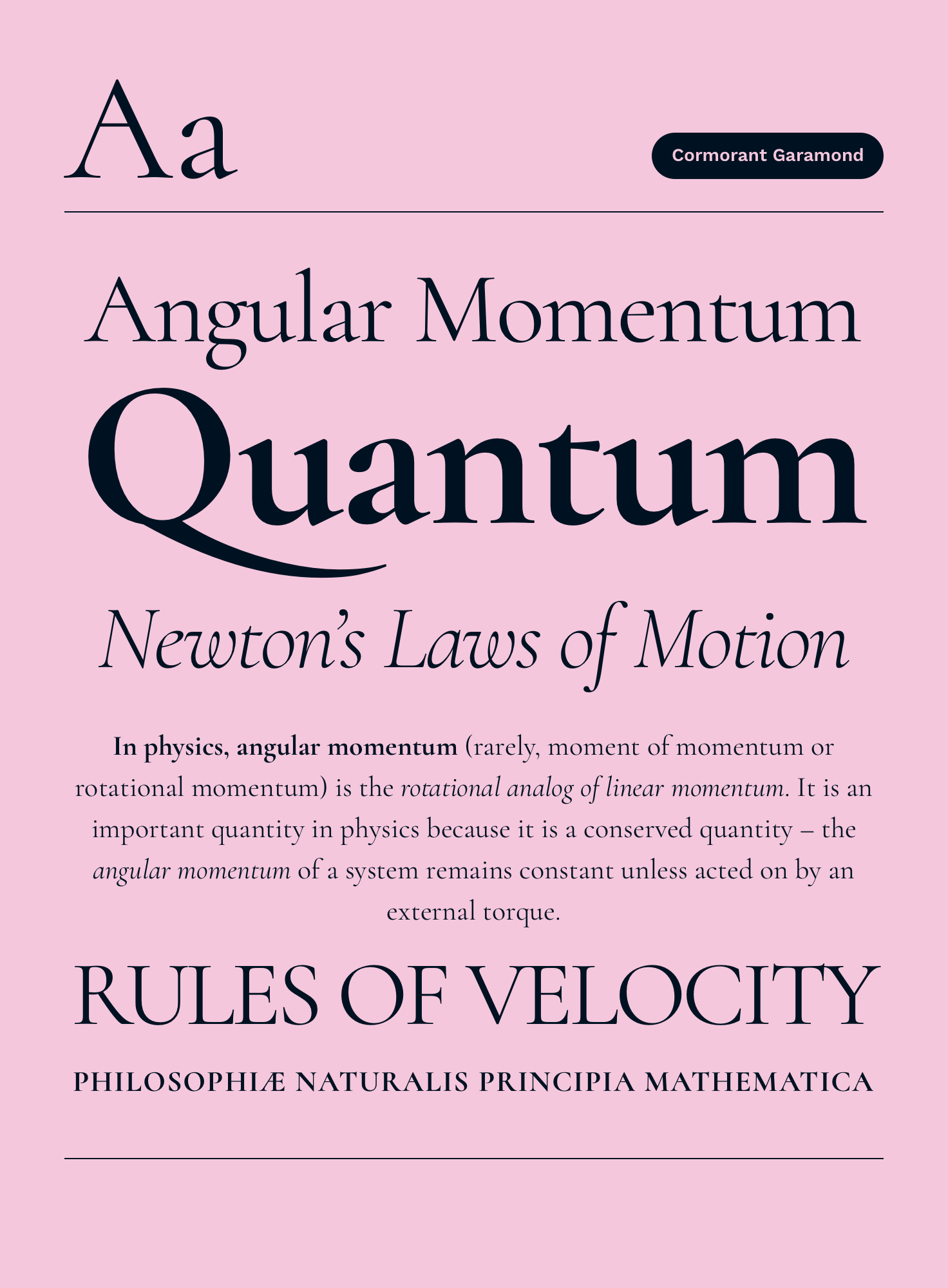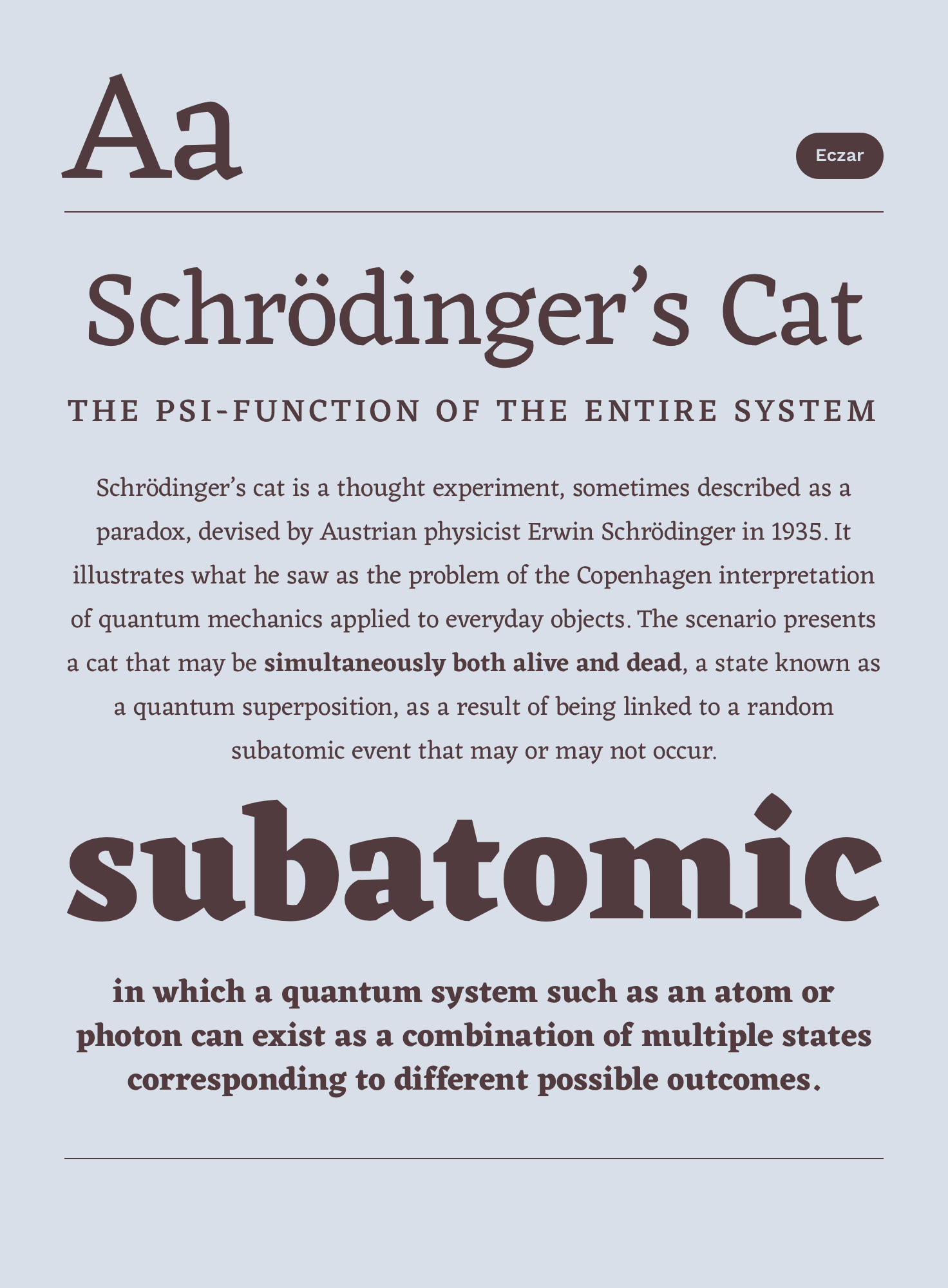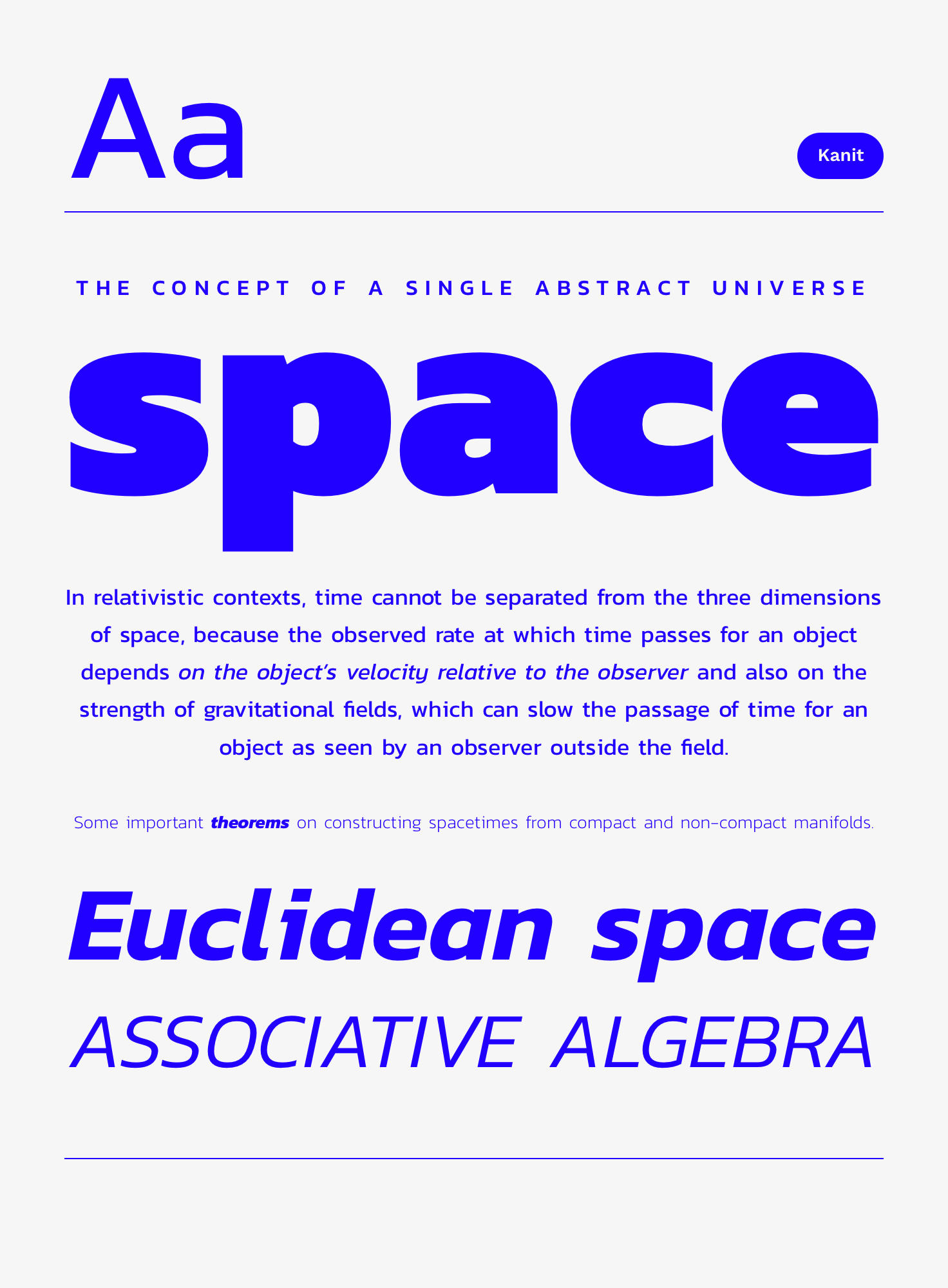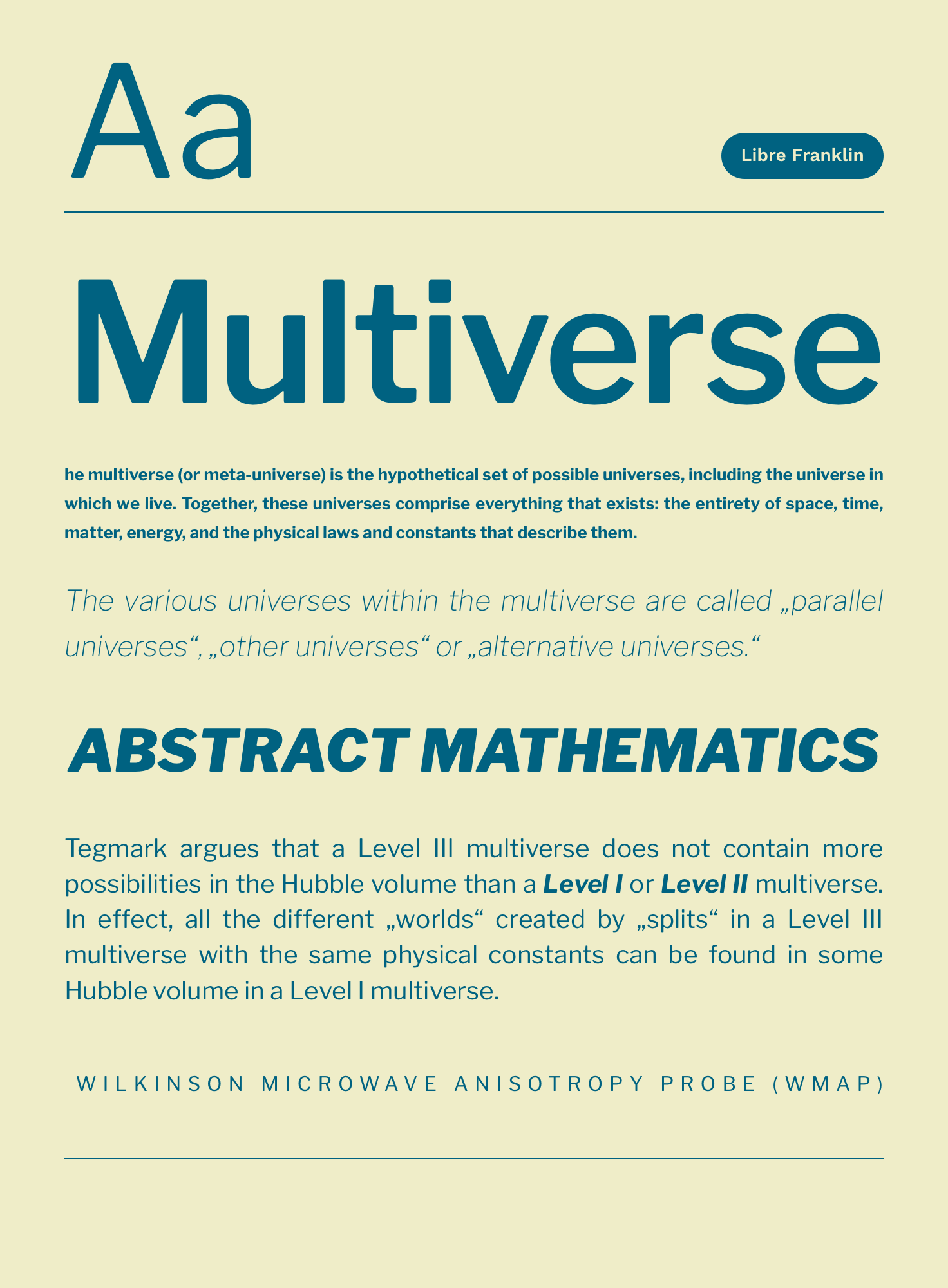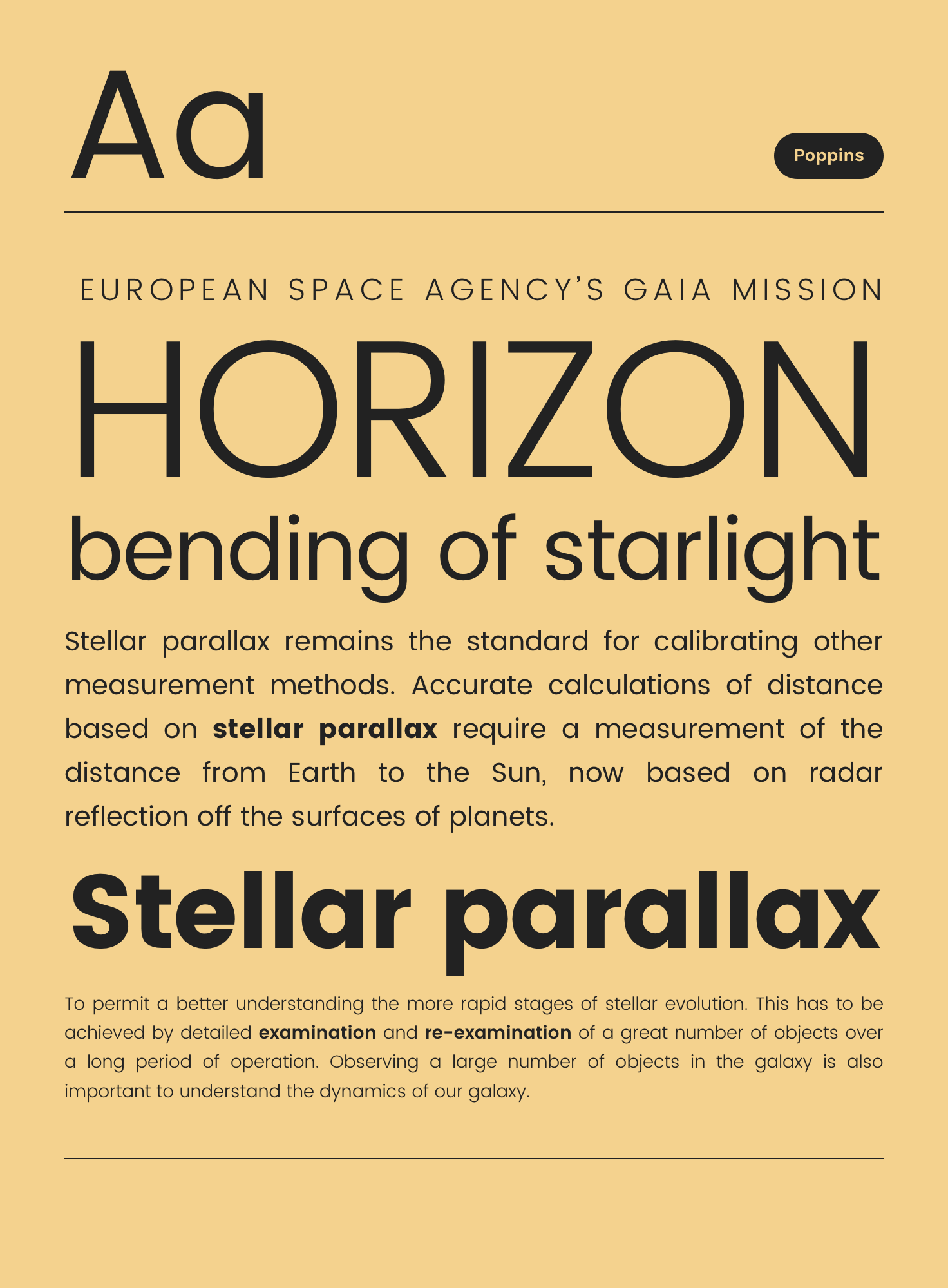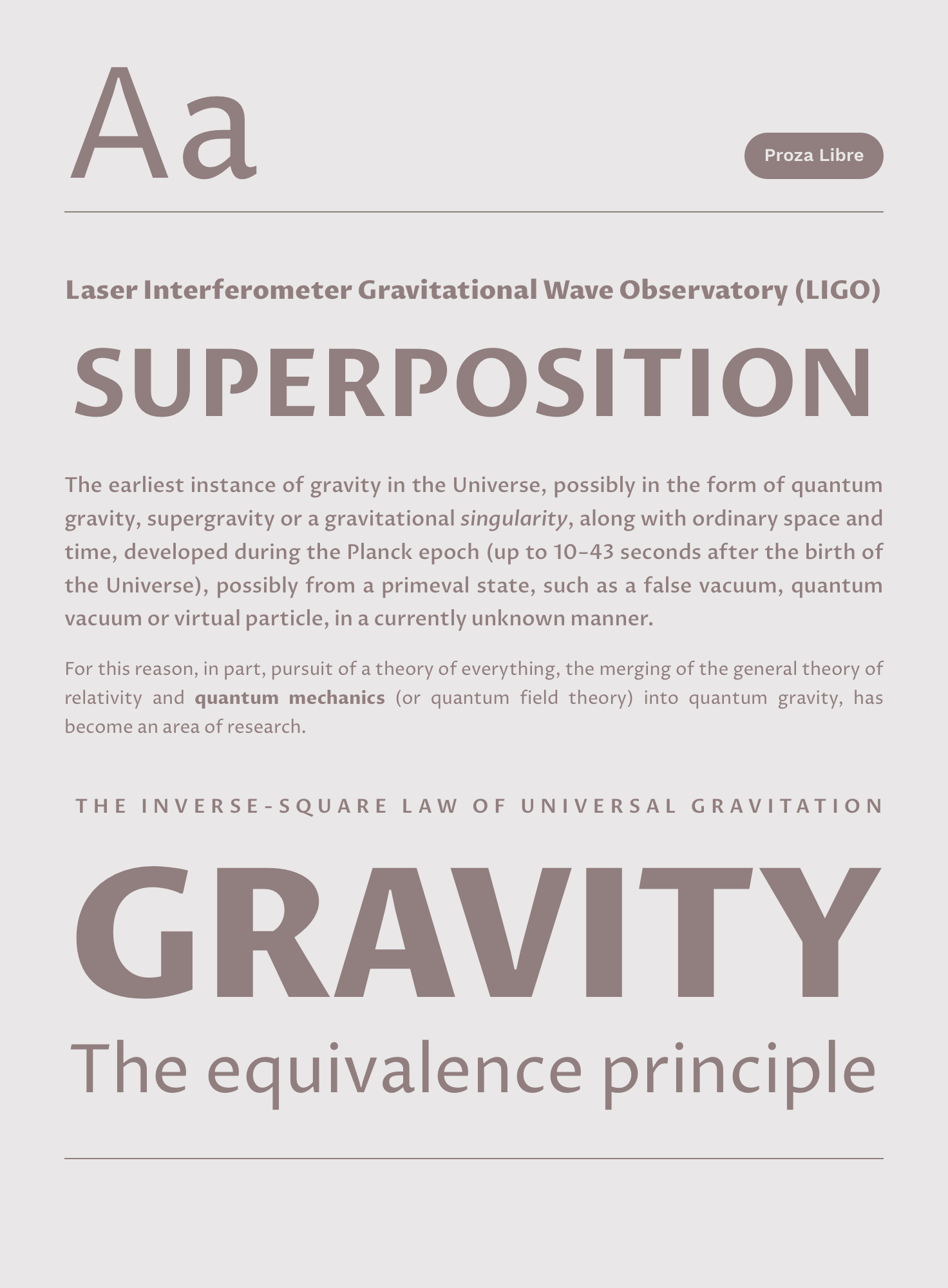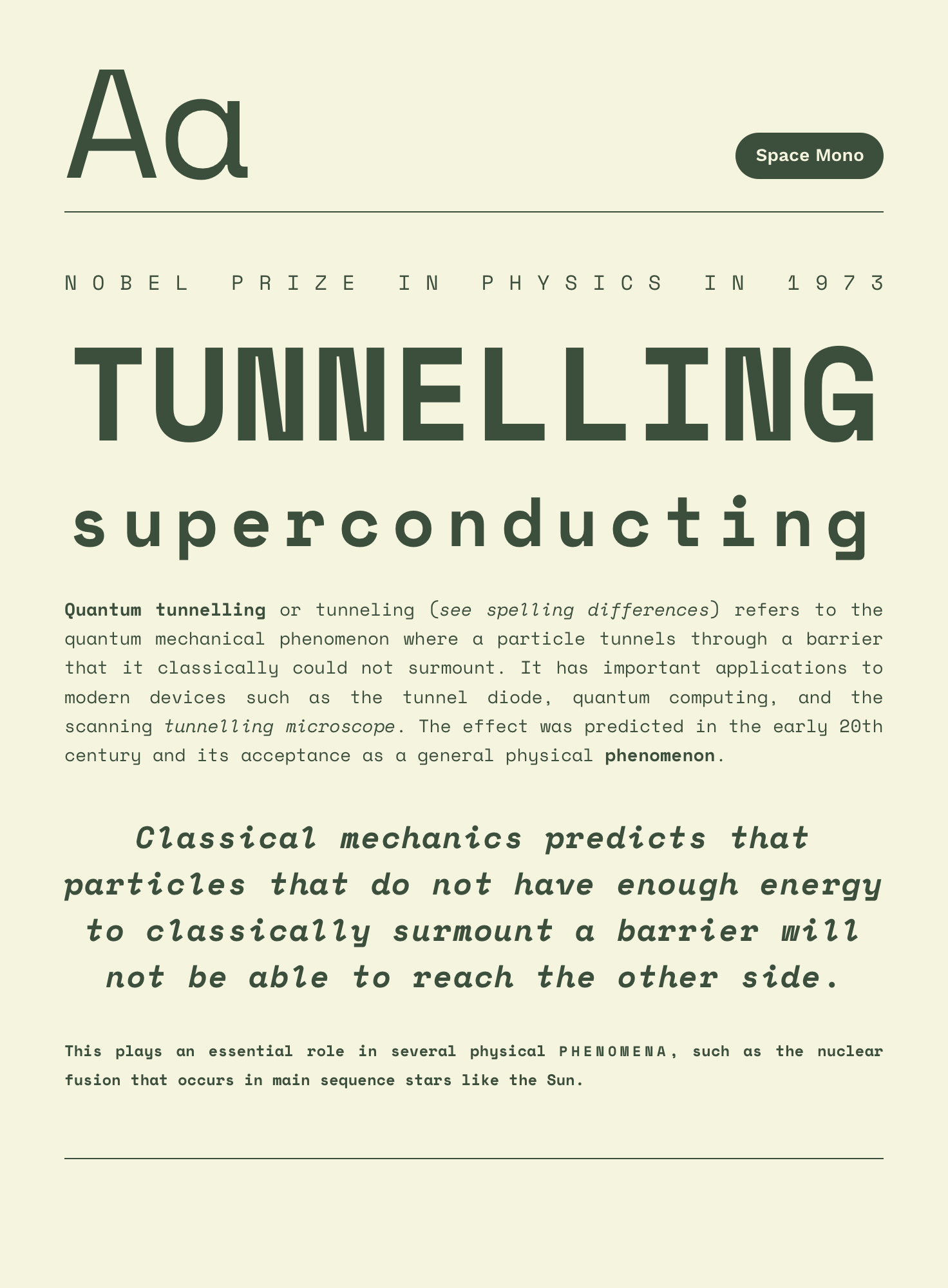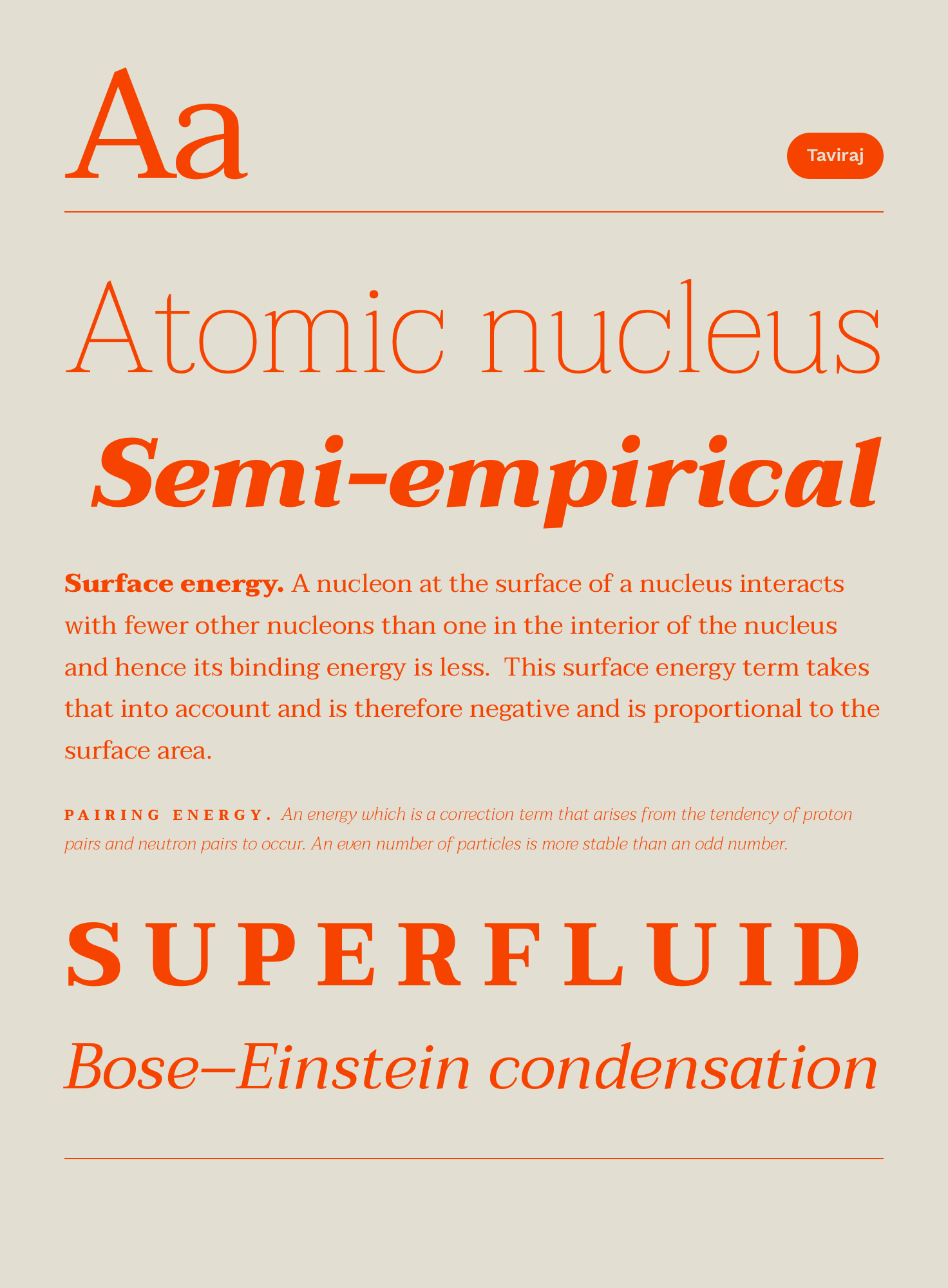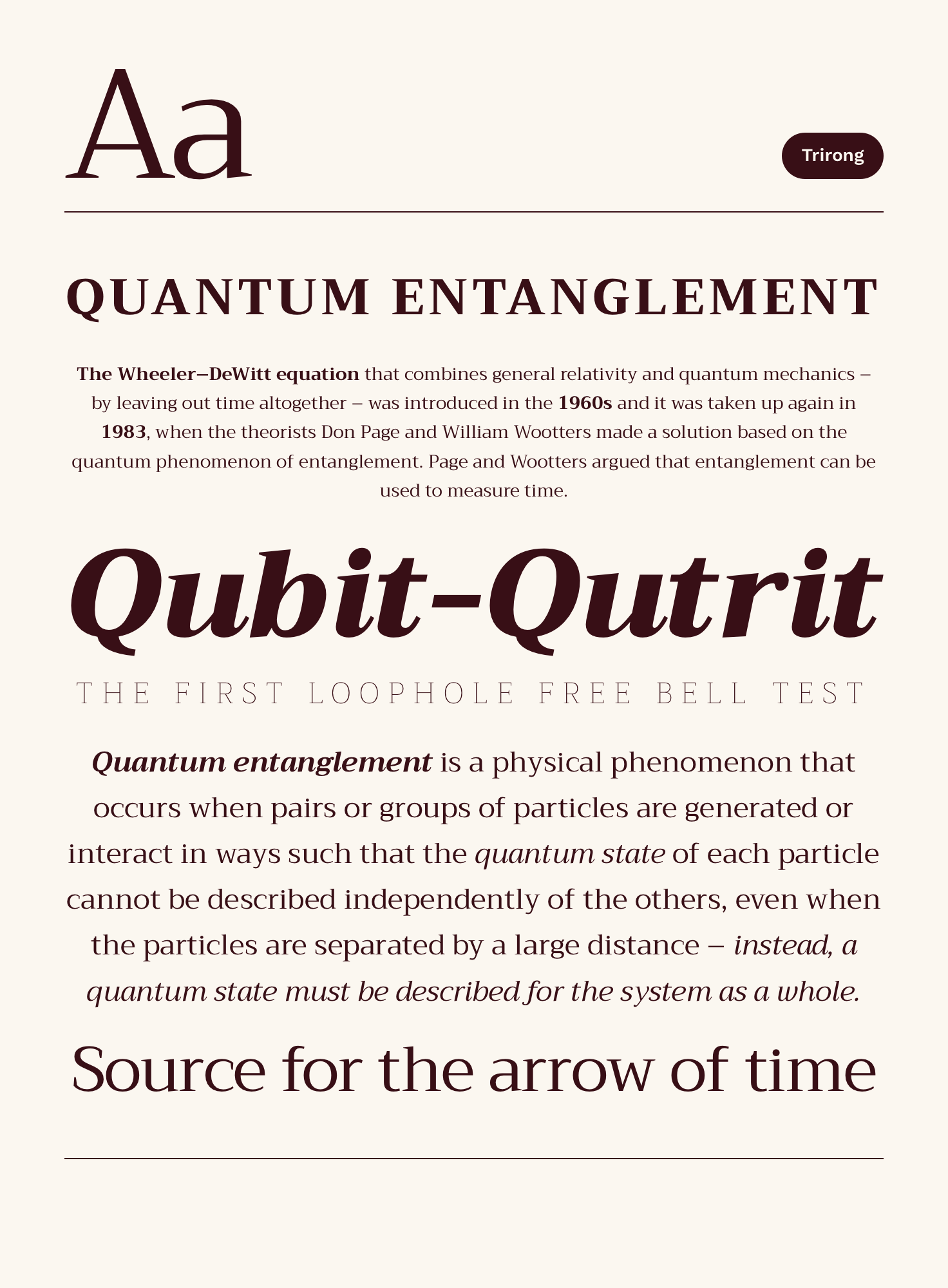
Es gibt jede Menge wunderschöne Google Fonts, aber da es inzwischen über 800 Schriften auf Google Fonts zur Auswahl gibt, kann es schwierig werden die passende Schrift für eine Webseite zu finden. Viel zu oft sieht man die gleichen Schriften im Einsatz, daher haben wir eine Liste weniger häufig verwendeter Google Fonts für dich zusammen gestellt. Hier sind unsere Google Fonts Favoriten, die du in 2017 unbedingt ausprobieren solltest.
1. Cormorant Garamond
Das Besondere an der Cormorant Garamond (neben dem Fakt, dass es eine sehr schöne, elegante Serifenschrift ist) ist, dass die Schrift eine große Anzahl an verschiedenen Schriftschnitten hat. Es gibt insgesamt 45 verschiedene Versionen der Schrift, einen Überblick findet man auf der Bēhance Seite der Schrift. Wir haben Cormorant Garamond auch im neuesten Designstil (siehe Live Demo Ruapuke) unseres Uku-Themes verwendet.
2. Proza Libre
Proza Libre ist die kostenlose Light-Version der Schrift Proza von Jasper de Waard (vom Bureau Roffa), eine von der Garamond Sans inspirierte elegante serifenlose Schrift. Die Schrift ist sehr angenehm lesbar als Fließtext und hat einen eleganten Stil in Titelschriftgrößen. Im Blogbeitrag “Proza’s Story” auf I Love Typography kannst du mehr über die Entstehungsgeschichte von Proza lesen.
3. Trirong
Trirong ist eine markante Serifenschrift mit 16 Schriftstilen der thailändischen Font Foundry Cadson Demak. Die Schrift ist recht breit und rund, ein Stil der der thailändischen Schrift nachempfunden ist. Die Schrift ist durch ihre Breite sehr gut als Fließtext lesbar.
4. Libre Franklin
Libre Franklin ist eine Neuinterpretation der klassischen amerikanischen Sansserif-Schrift “Morris Fuller Benton classic” der argentinischen Type Foundry Impallari Type. Libre Franklin hat 18 Schriftschnitte, was die Schrift sehr flexibel im Einsatz macht.
5. Taviraj
Auch Taviraj ist eine Schrift von Cadson Demak aus Thailand. Die moderne, vielseitig einsetzbare Serifenschrift mit 18 Schriftschnitten ist ähnlich wie Trirong von den klassischen, runden geschwungenen Buchstaben der thailändischen Schrift inspiriert.
6. Eczar
Die markante, eckige Schrift Eczar von Rosetta lässt sich wunderschön als Schrift für besondere Überschriften oder kleinere Textabsätze einsetzen. Besonders die fetten Schriftschnitte sind sehr charakterstark. Eczar gibt es in 5 Schriftschnitten.
7. Work Sans
Work Sans ist eine unserer persönlichen serifenlosen Schrift-Favoriten, die wir auch in unserem 2016 Elmastudio-Webdesign eingesetzt haben. Durch die Breite der Schrift ist Work Sans sehr gut lesbar und eignet sich daher besonders gut für Fließtexte im Web. Die Schrift von Wei Huang hat neun unterschiedliche Schriftschnitte.
8. Space Mono
Space Mono ist eine Monospace-Schrift von Colophon Foundry, die sich für individuelle Überschriften oder Meta-Text auf Webseiten besonders gut eignet. Die Schrift hat vier Schnitte, u.a. eine italic und bold italic.
9. Poppins
Poppins ist eine modern wirkende, geometrische serifenlose Schrift, die sowohl für Fließtexte, als auch für Überschriften sehr gut verwendet werden kann. Poppins ist von der Indian Type Foundry entwickelt und kann daher auch in Devanagari Schriftzeichen (für Sanskrit oder Hindi) genutzt werden. Poppins setzen wir ebenfalls im Uku-Theme ein (im serif- und neo-Designstil).
10. Kanit
Auch Kanit (“kanit” bedeutet Mathematik auf Thailändisch) ist eine Schrift von Cadson Demak aus Bangkok. Die serifenlose Schrift kann besonders gut auch für kleine Schriftgrößen eingesetzt werden. Mit ihren 18 Schriftschnitten kann die Schrift sehr vielseitig genutzt werden.
11. Yrsa
Yrsa von Rosetta ist mit ihren fünf Schriftschnitten und Support für über 45 Sprachen eine an leicht von der Merriweather inspirierte Schrift und eine erfrischende, etwas moderner wirkende Alternative zu dieser doch sehr häufig verwendeten Schrift.
12. Abhaya Libre
Die elegante Serifenschrift Abhaya Libre von Mooniak, einem Designstudio aus Sri Lanka ist die kostenlose Alternative zur beliebtesten Sinhala Schrift “FM Abhaya”. Die lateinischen Buchstaben sind dem Sinhala-Schriftbild nachempfunden. Abhaya Libre hat fünf Schriftschnitte.
Vielen Dank für die Tipps! Von dieser Auswahl gefallen mir insbesondere zwei Schriftarten, nämlich “Cormorant Garamond” und “Libre Franklin”. Benutze sie beide zum Schreiben auf dem Desktop. Für einen Output in gedruckter Form ist Cormorant Garamond allerdings ein bisschen zu verspielt, insbesondere für offizielle und formale Dokumente (das große “Q” vor allem). Libre Franklin eignet sich hierfür natürlich ohne Probleme. Für die Homepage habe ich beide noch nicht ausprobiert.